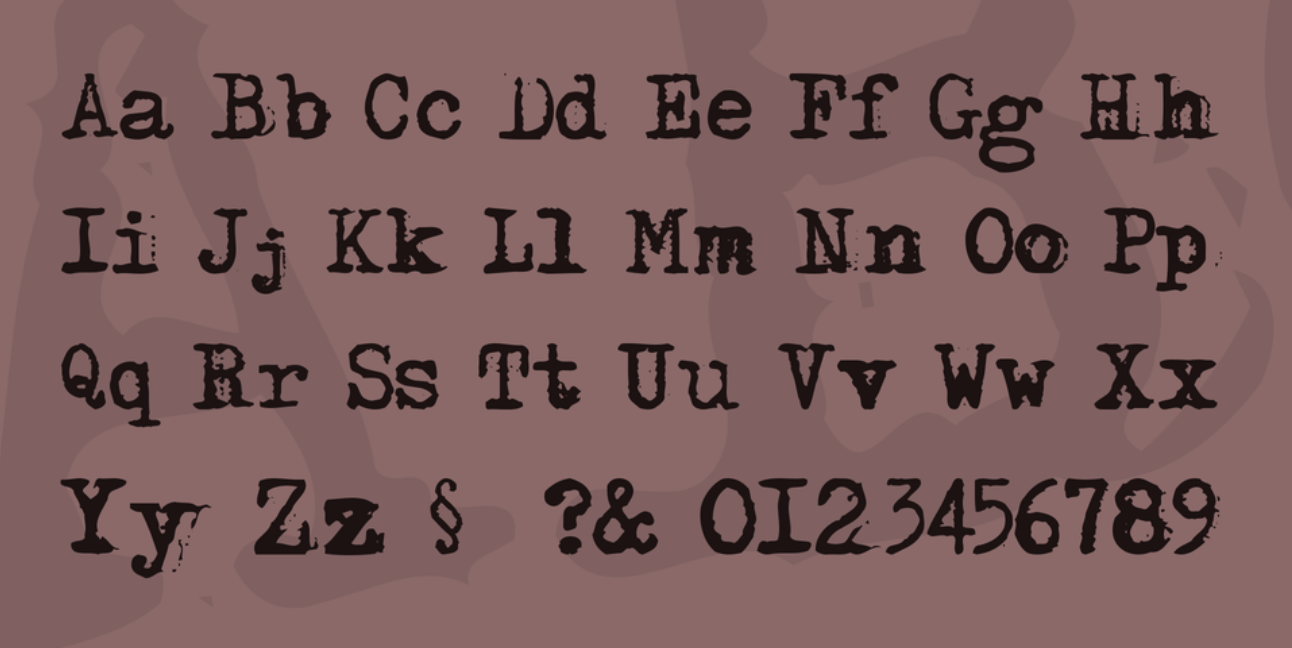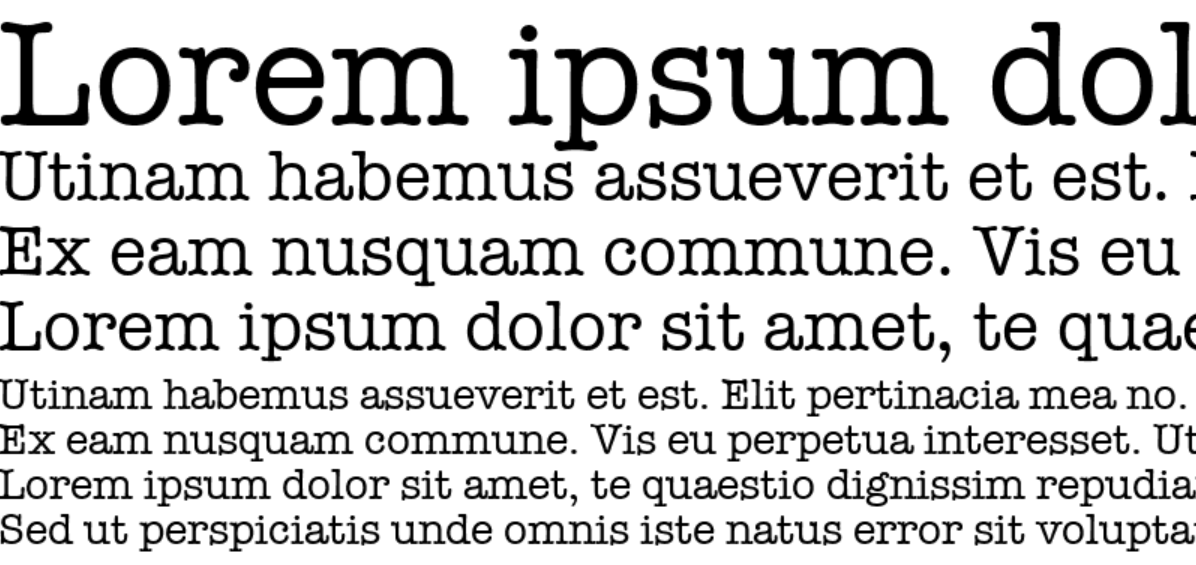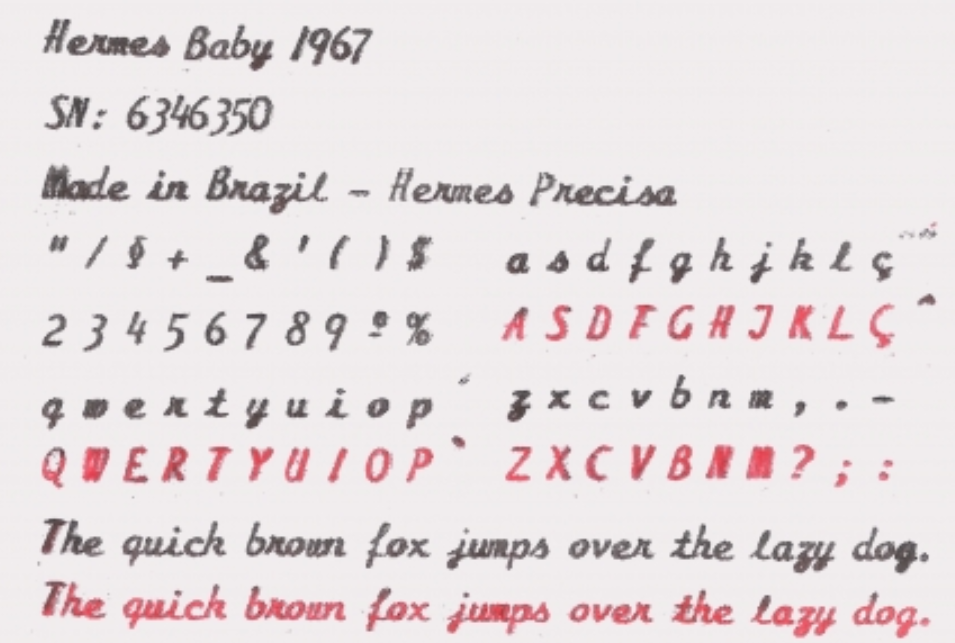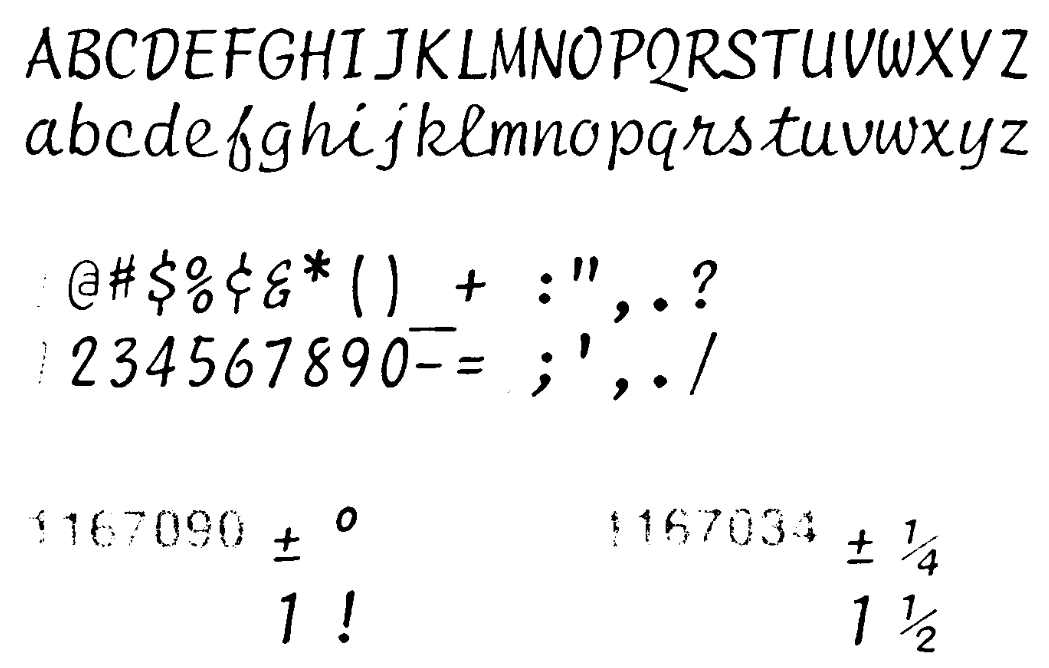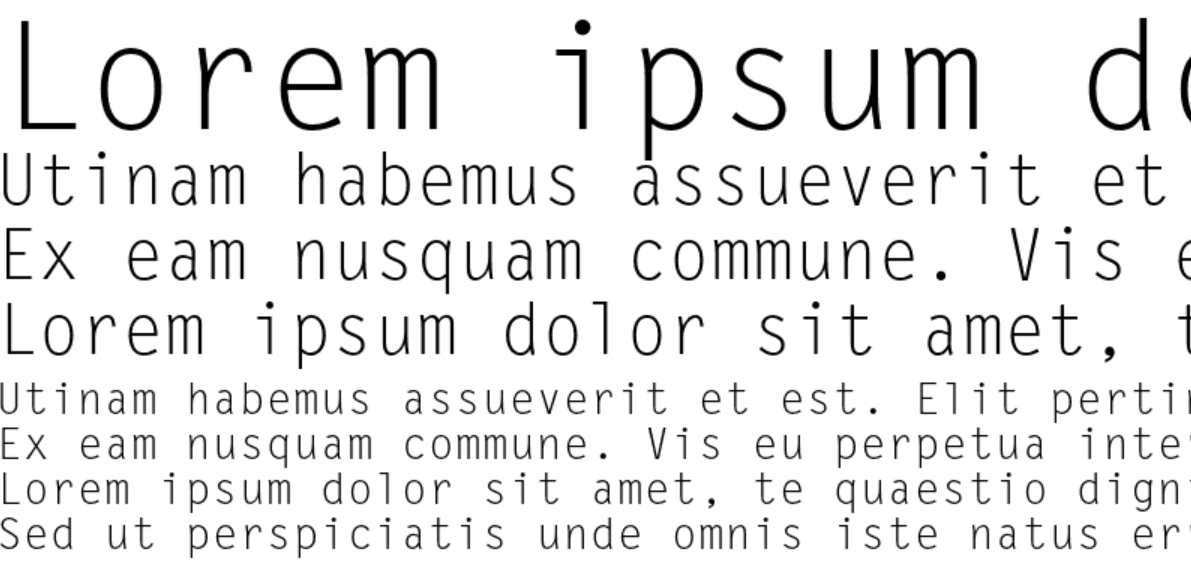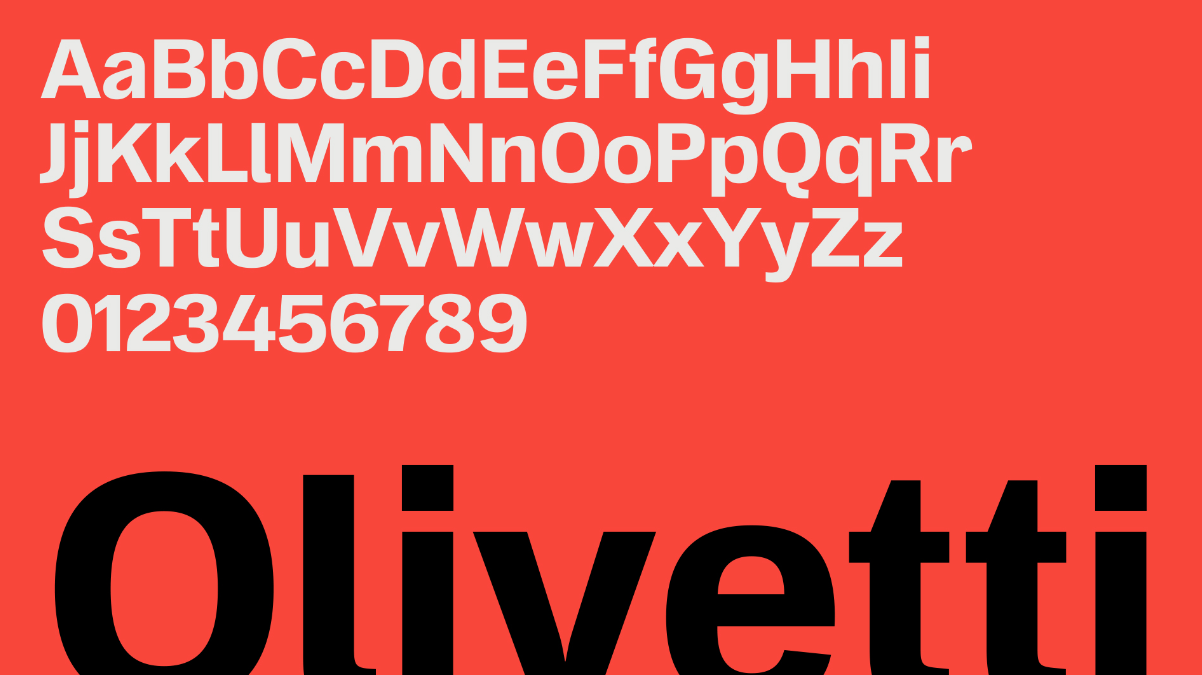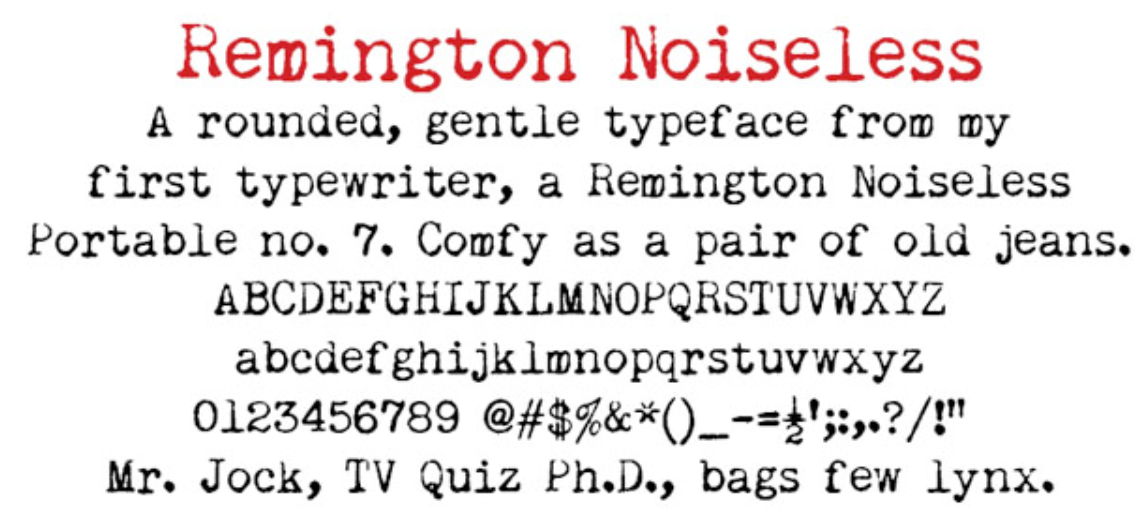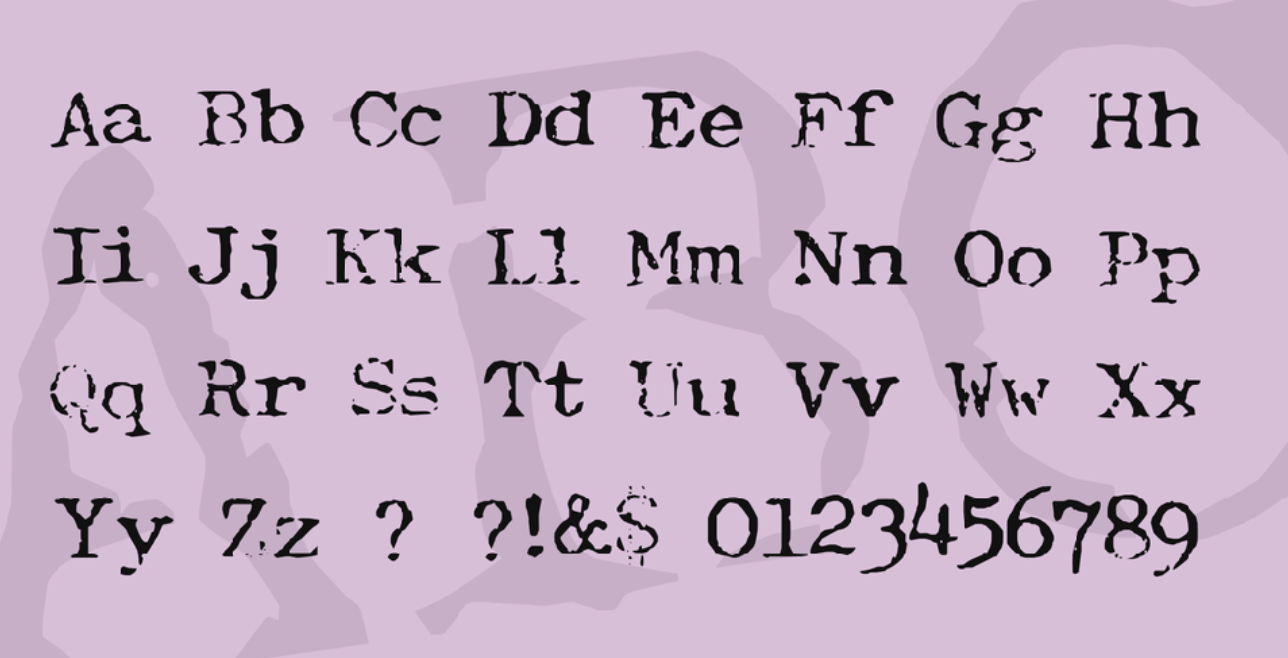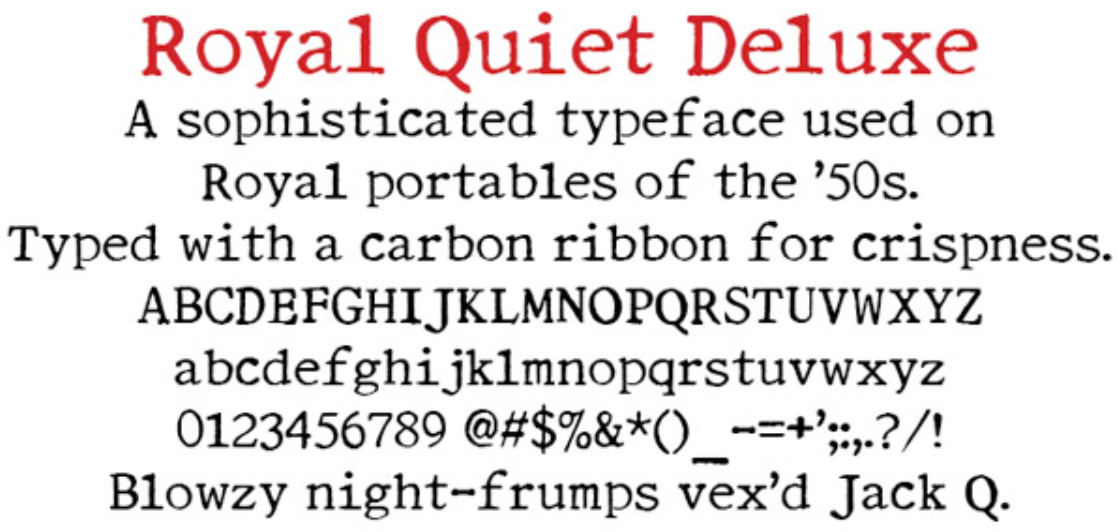
17 Jenis Font Mesin Ketik (Typewriter Font) Gratis
Font mesin ketik, dengan nuansa klasik dan sentuhan nostalgia, telah menjadi pilihan populer di berbagai bidang desain dan penulisan.
Dalam artikel ini, kita akan mengeksplorasi 17 jenis font mesin ketik yang berbeda, masing-masing dengan karakteristik uniknya, pembuatnya, dan penggunaan umumnya.
1. American Typewriter
Dibuat oleh Joel Kaden dan Tony Stan, American Typewriter adalah font yang meniru tampilan mesin ketik klasik. Sering digunakan dalam desain grafis untuk menciptakan kesan vintage.
2. Courier
Desain oleh Howard “Bud” Kettler pada tahun 1955, Courier adalah font Typewriter yang paling dikenal. Digunakan secara luas dalam skenario hukum dan skrip skenario karena legibilitasnya.
3. Prestige Elite
Prestige Elite, yang dibuat oleh Clayton Smith pada tahun 1953, menawarkan tampilan yang lebih ramping dan modern. Sering digunakan dalam dokumen bisnis dan administratif.
4. Letter Gothic
Desain oleh Roger Roberson, Letter Gothic adalah font yang dirancang untuk IBM. Cocok untuk dokumen teknis karena gaya huruf yang jelas dan mudah dibaca.
5. Olympia
Terinspirasi oleh font klasik, Olympia sering digunakan dalam karya sastra dan puisi karena nuansa klasiknya.
6. Smith Corona
Mengambil nama dari produsen mesin ketik terkenal, font Smith Corona memiliki tampilan tradisional yang ideal untuk proyek-proyek retro.
7. Underwood Champion
Didasarkan pada mesin tik, font ini menyampaikan estetika awal abad ke-20 yang sempurna untuk poster dan materi iklan.
8. Remington Noiseless
Remington Noiseless, dengan gaya uniknya, sering digunakan dalam desain buku dan majalah untuk menciptakan nuansa vintage.
9. Royal Quiet Deluxe
Font ini mengambil inspirasi dari mesin tik klasik, Royal Quiet Deluxe populer dalam desain undangan dan stationary karena elegansinya.
10. Hermes Baby
Dibuat berdasarkan desain mesin tik, Hermes Baby dikenal dengan kesederhanaan dan keefektifannya. Cocok untuk penerbitan dan dokumen akademik.
11. IBM Selectric
Terinspirasi oleh mesin tik legendaris, IBM Selectric font menawarkan tampilan yang bersih dan profesional, sering digunakan dalam laporan korporat dan komunikasi bisnis.
12. Olivetti
Mengambil nama dari produsen mesin ketik Italia, Olivetti, font ini memiliki tampilan Eropa yang khas, ideal untuk penerbitan dan materi desain.
13. Royal 200
Didasarkan pada mesin ketik Royal 200, font ini menghadirkan estetika vintage yang khas, sering digunakan dalam proyek-proyek seni dan desain retro.
14. Smith Premier
Mengambil inspirasi dari mesin ketik Smith Premier, font ini dikenal dengan tampilannya yang klasik dan elegan, cocok untuk surat resmi dan undangan.
15. Triumph
Font Triumph, yang mengambil inspirasi dari mesin ketik Triumph, menawarkan tampilan yang tajam dan terfokus, ideal untuk publikasi teknis dan dokumentasi.
16. Adler
Terinspirasi oleh mesin ketik Adler, font ini memiliki tampilan yang unik dan serbaguna, sering digunakan dalam pemasaran dan materi promosi.
17. Facit
Didasarkan pada desain mesin ketik Facit, font ini menawarkan tampilan yang modern dan minimalis, populer dalam desain web dan media digital.
Kesimpulan
Font Typewriter menghadirkan nuansa nostalgia sambil tetap relevan dalam desain modern. Mereka menawarkan berbagai gaya dan fungsi, dari kebutuhan korporat hingga proyek kreatif, membuktikan bahwa gaya klasik ini masih memiliki tempat yang penting di dunia digital saat ini.